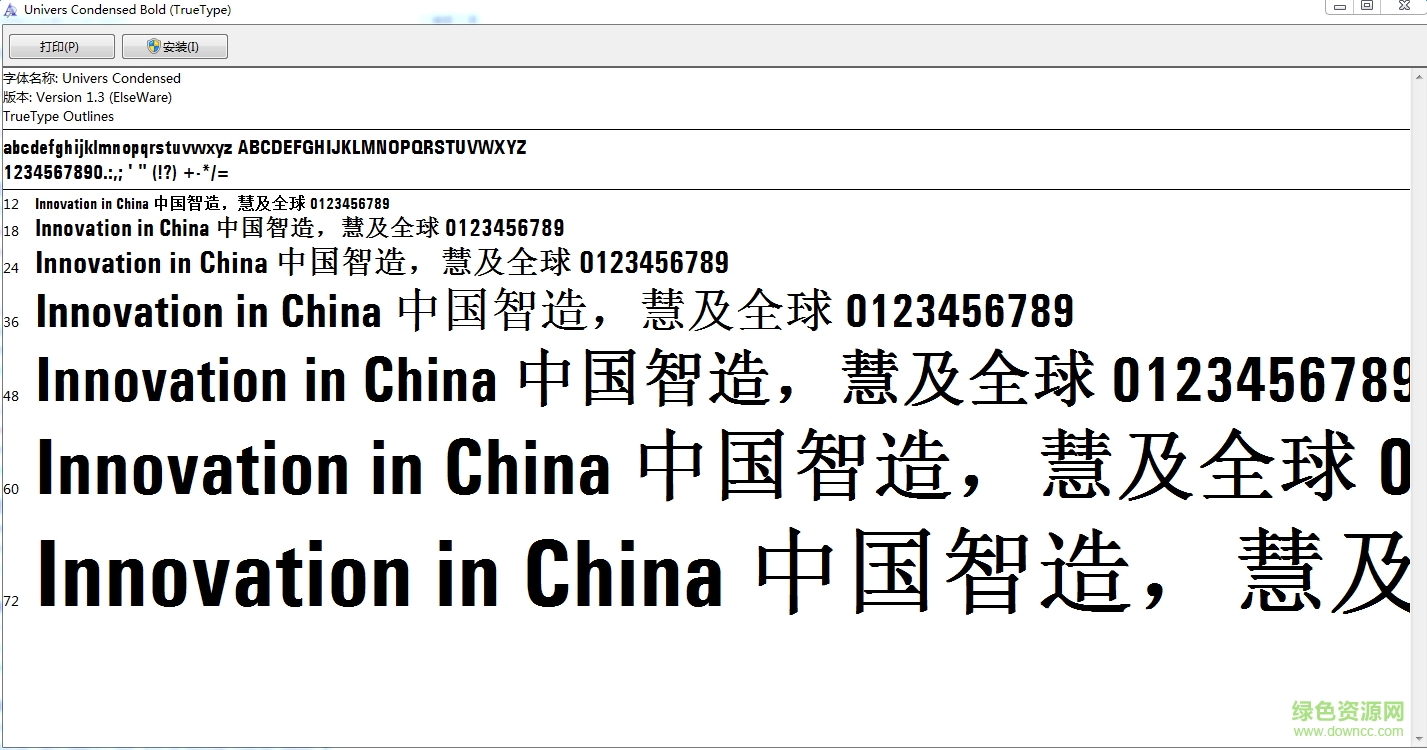
univers condensed bold字體是一款粗壯醒目的英文字體,該字體結(jié)構(gòu)嚴(yán)謹(jǐn),筆畫穩(wěn)重,字形挺拔,易讀性和欣賞性兼?zhèn)?,有需要的小伙伴快來下載收藏吧!
【粗與細(xì)】
筆畫粗則渾厚、濃重、有力,如雷霆萬鈞;筆畫細(xì)則單薄、輕巧、纖弱,似弱柳扶風(fēng),這是一種最直接粗淺的觀感。
粗筆畫字體在排版上會(huì)形成高密度的文本塊,這是因?yàn)楣P畫加粗,字體的負(fù)空間就會(huì)減小,視覺面積加重,產(chǎn)生一種壓迫感,進(jìn)而形成視覺重心,產(chǎn)生強(qiáng)調(diào)的作用。所以粗體字經(jīng)常用于標(biāo)題和標(biāo)語上,占據(jù)顯眼的位置,產(chǎn)生強(qiáng)調(diào)的作用。
如果說粗體是彪形大漢的一聲斷喝,那么細(xì)體則是小家碧玉的吳儂軟語,娓娓道來。細(xì)筆畫字體在視覺面積上較淡較輕,縮小了視覺面積后,筆畫負(fù)空間增大,結(jié)構(gòu)顯得疏朗清透,較小的視覺分量亦不會(huì)讓讀者產(chǎn)生壓迫感。